Denominał
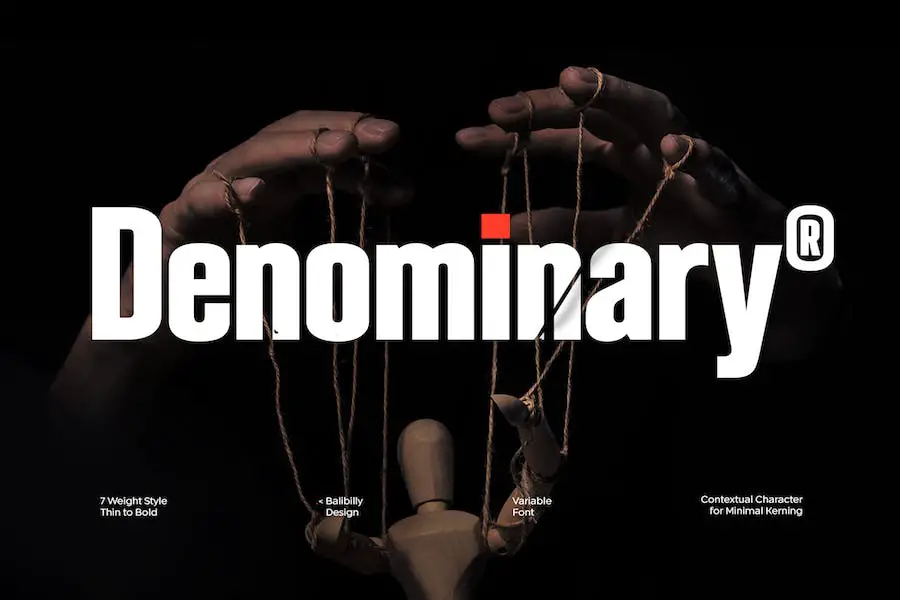
Umberland Slab to krój pisma, który wnosi wyrafinowanie, ekskluzywność i wyrafinowanie do każdego projektu. Zaawansowana, automatycznie aktywowana funkcja alternatywnych kontekstów zapewnia przewagę konkurencyjną w dziedzinie projektowania.
Ta funkcja automatycznie dostosowuje odstępy między znakami, zapewniając optymalne odstępy między literami.
Wykonany ze starannością i dbałością o szczegóły, Umberland Slab ma naturalny głos i płynność, dzięki czemu jest zarówno czytelny, jak i stylowy. To krój pisma, który opowiada historię precyzji, piękna i wyróżnienia.
KABOORE
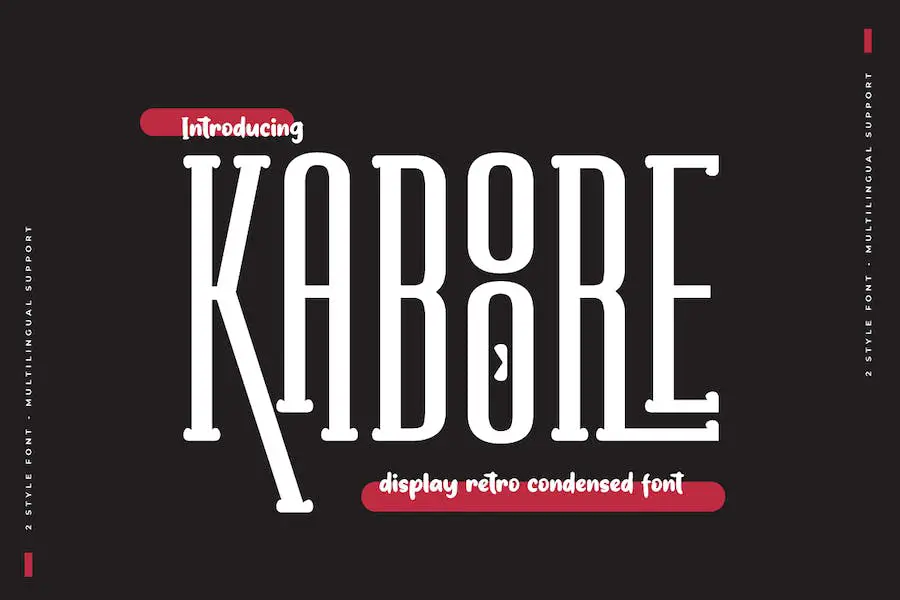
Kaboore to skondensowana czcionka w stylu retro, która nadaje Twoim projektom czysty i nowoczesny charakter. Dzięki mocnemu i niepowtarzalnemu wyglądowi ta czcionka idealnie nadaje się do przyciągania uwagi przyciągającymi wzrok tytułami i nagłówkami.
Ma gruby i solidny wygląd, zapewniający czytelność nawet przy średnich i dużych rozmiarach czcionek. Kaboore jest dostępny w dwóch stylach, płytowym i sans, i jest wzbogacony o opcjonalne ligatury dla dodatkowej wszechstronności. Jeśli chcesz, aby Twoje projekty były niezwykłe, ta czcionka jest koniecznością.
Lorida
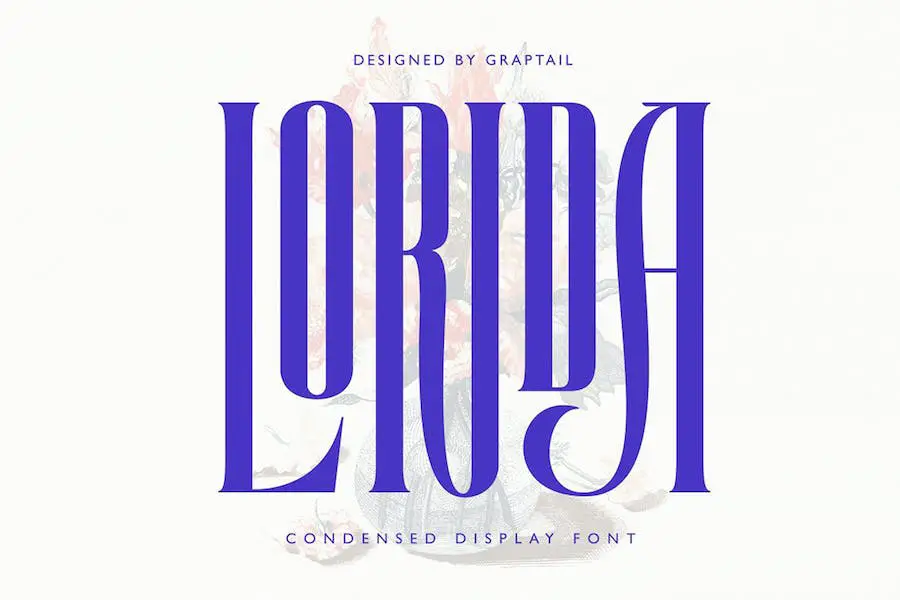
Lorida Condensed Display to oszałamiająca czcionka szeryfowa, która dodaje elegancji każdemu projektowi. Dzięki unikalnym ligaturom dla każdej kombinacji liter przyciąga wzrok i robi wrażenie.
Ta czcionka jest wszechstronna, dzięki czemu idealnie nadaje się do szerokiej gamy projektów, w tym logo, kart okolicznościowych, plakatów i innych. Jego kompaktowy i solidny styl sprawia, że wyróżnia się i przyciąga uwagę.
Niezależnie od tego, czy tworzysz tytuły filmów, nagłówki blogów czy układy czasopism, Lorida to idealny wybór, który ulepszy Twój projekt.
Miętowy marzec
Minty March to urocza, odręczna czcionka, która dodaje uroczego akcentu każdemu projektowi. Niezależnie od tego, czy tworzysz kartki, zaproszenia, logo czy zaproszenia urodzinowe, ta skondensowana czcionka szeryfowa idealnie nadaje się do nadania osobistego, ręcznie robionego charakteru.
Czcionka zawiera wszystkie standardowe znaki, zarówno małe, jak i wielkie, a także cyfry i znaki interpunkcyjne. Zawiera nawet ligatury i znaki międzynarodowe, dzięki czemu jest wszechstronny w przypadku różnych języków i potrzeb projektowych.
Dzięki swojemu fantazyjnemu stylowi i wszechstronności Minty March doskonale łączy się z czcionkami skryptowymi, umożliwiając tworzenie unikalnych i przyciągających wzrok projektów. Niezależnie od tego, czy jesteś grafikiem, który chce ulepszyć swoje projekty, czy po prostu kochasz piękną typografię, ta czcionka jest koniecznością.
Wapń
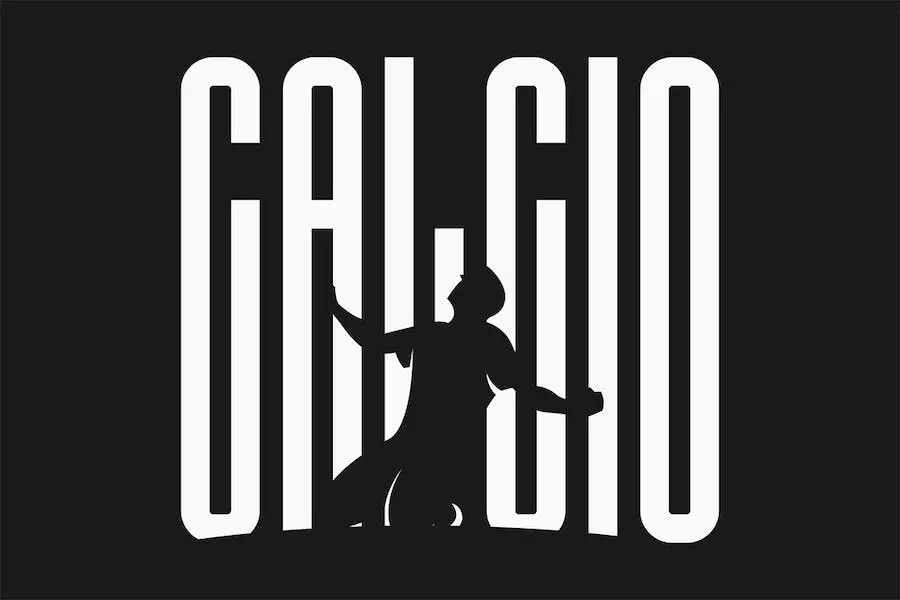
Calcio to niesamowita czcionka, która przeniesie Twoje projekty na wyższy poziom. Dzięki wyjątkowo skondensowanym i minimalistycznym znakom Calcio idealnie nadaje się do tworzenia oszałamiających logo, wizytówek, układów czasopism, zaproszeń, nagłówków, a nawet grafik na dużą skalę.
Ta czysta czcionka bezszeryfowa zawiera zarówno wielkie, jak i małe litery pisane wielkimi literami, a także cyfry i różne symbole. Zawiera także pomocny plik, który pomoże Ci w trakcie.
Ponadto dzięki wielojęzycznej obsłudze różnych języków możesz używać Calcio do ulepszania swoich projektów bez względu na to, gdzie jesteś na świecie. Więc po co czekać? Zacznij crackować z Calcio i zobacz magię rozwijającą się w Twoich projektach.